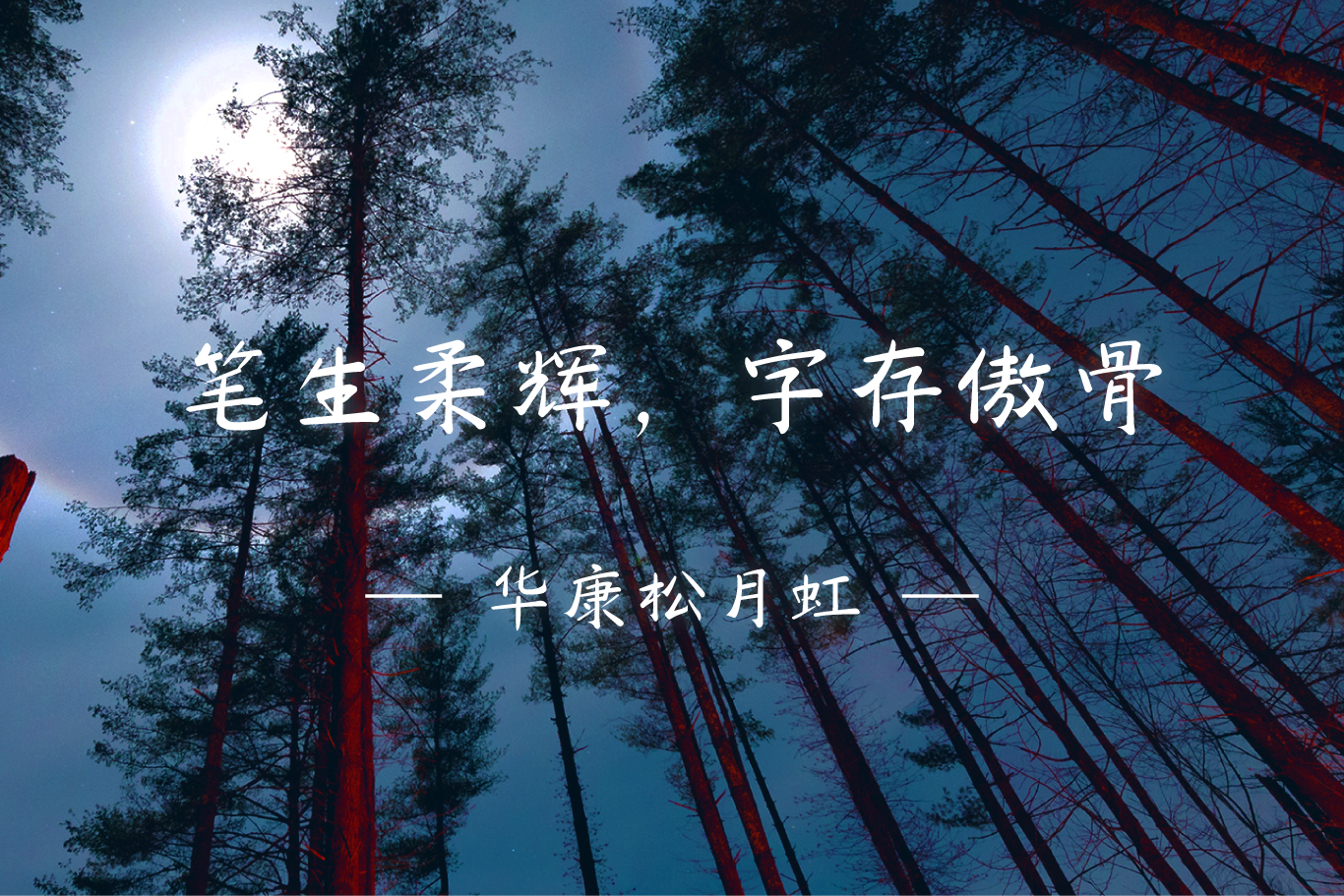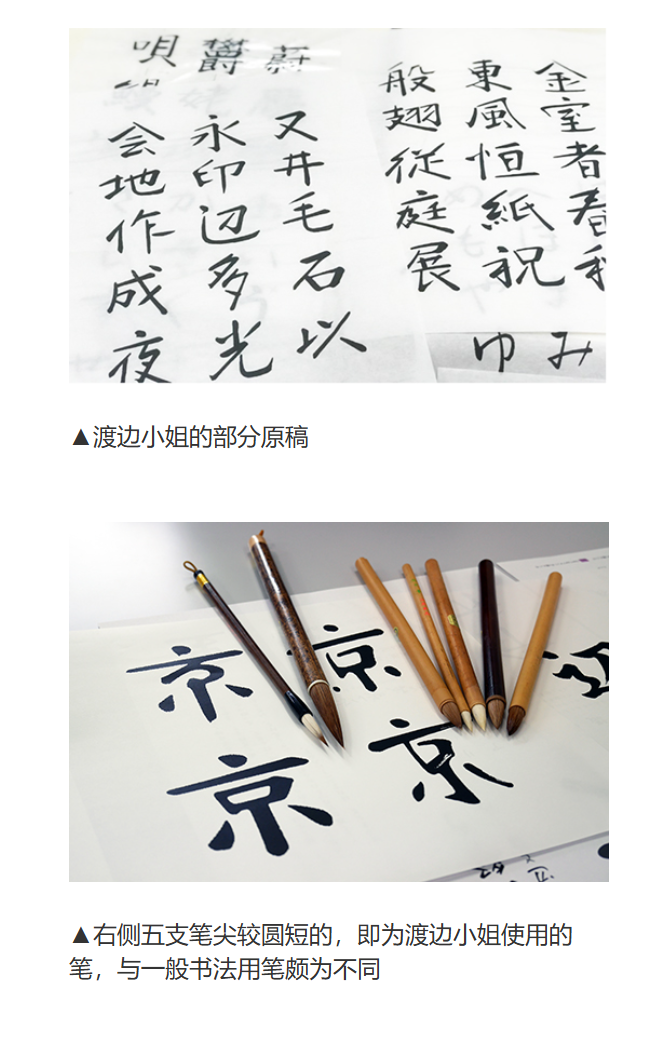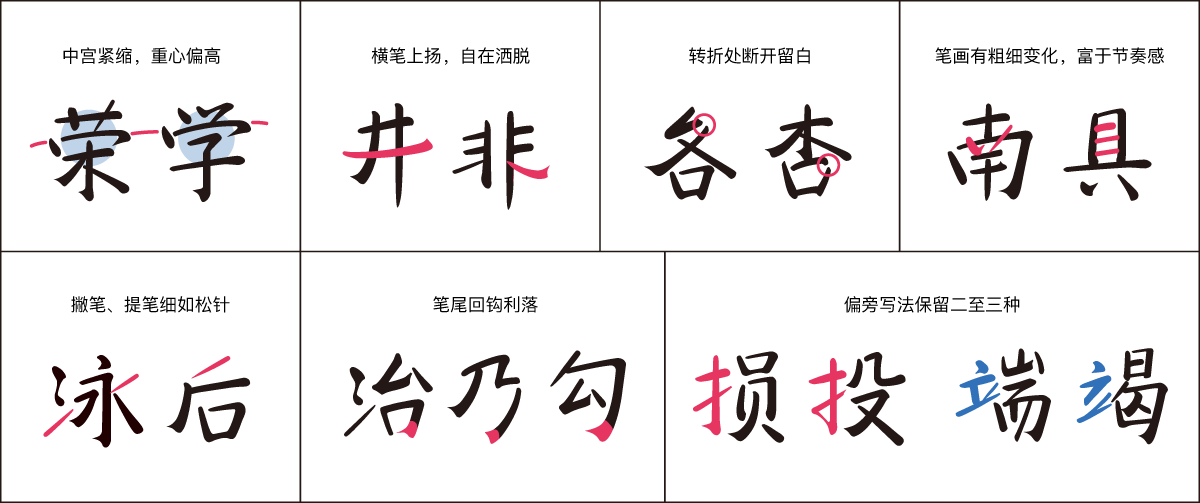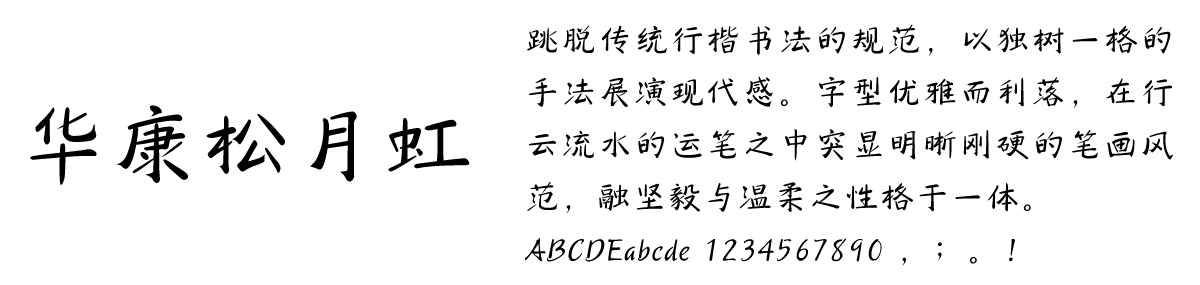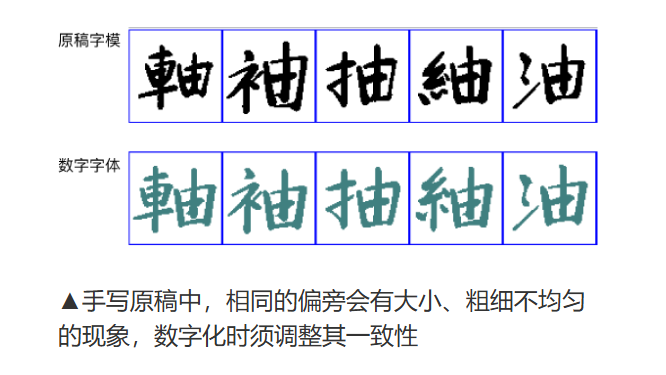
DynaFont书法字体──华康松月虹
笔生柔辉,字存傲骨
谁说书法提按顿挫、起收转折一定要按规矩来?换枝不一样的笔、用不一样的笔法和书写习惯,也能将传统行楷书法改头换面,穿上一袭“时尚感”!
换骨脱胎 写出书法的现代灵魂
华康松月虹的诞生,是两组不同基因的融合:它既来自毛笔与书法,却在孕育之初就注入了现代文字设计的思维。它的身世渊源于2013年华康公司举办的“字体设计大赛 书法部门”,由日本书法家兼文字设计师渡边美里小姐获得最优秀奖而来。随后,华康公司决定将这款备受好评的字体开发成数字字体,于是开启了渡边小姐的手写长征之旅。
渡边小姐以行楷书风为基础,自由地游转笔锋,改变了传统行楷笔法,形成个性鲜明的笔画样貌。又选用晕墨效果良好的笔,写在宣纸的光滑面上,让涨开的墨能被受墨度较低的纸面收束,写出来的字迹既能表现出书法的墨韵,却又让笔画显得平滑而硬朗,表现出干净洗练的现代感。
由此,渡边小姐一笔一画,足足写了超过7000字,终于催生出了“华康松月虹”的雏形。
在数字与手写之间 字体设计师的造字秘技
尽管渡边小姐的原稿已相当完整,但要转化为数字字体上市,仍是漫长的挑战。
收到手书原稿之后,字体设计师必须从中挑拣、精心修整,才能制作成一套可用、好用的数字字体。而如何挑选、绘制笔画,再进行组字、修调,既要能忠于原始风格,又能兼顾数字字型的整体性与实用性,都得仰赖设计师长年的造字经验。
设计师提取这套字体独特的笔形来绘制数字笔画。例如,上扬出钩以连接竖画笔意的横笔、细如松针的撇笔、刻意断开的转折处、利落如刀的回钩等。由于手写字难免会有大小、偏旁、笔画粗细不均的情况,进行数字制作时,都需要仔细修调。此外,汉字与西文、符号的搭配,也须经反复的混排试验,才能调整到最适切的比例。
不过,为了保持灵活,兼顾一致性与人性,设计师也特别为相同的偏旁部首或某些笔画留下二至三种不同的写法,为这款字体带来丰富变化,避开了呆板的可能,留住了恰到好处的手写风味。
DynaFont松月虹的笔画特色
华康松月虹孕育自传统行楷书法,但挣脱书法规范,用独特写法展演出现代感。这款字体秀逸而利落,在流畅的运笔中可见刚硬的笔画风格,刚柔并济,宛如月光折射而出的虹彩,照亮了骨干傲立、枝叶飘舞的松树。无论何种类型的设计应用,都能通过华康松月虹带来优雅而清新的视觉感受。
华康松月虹字体范例